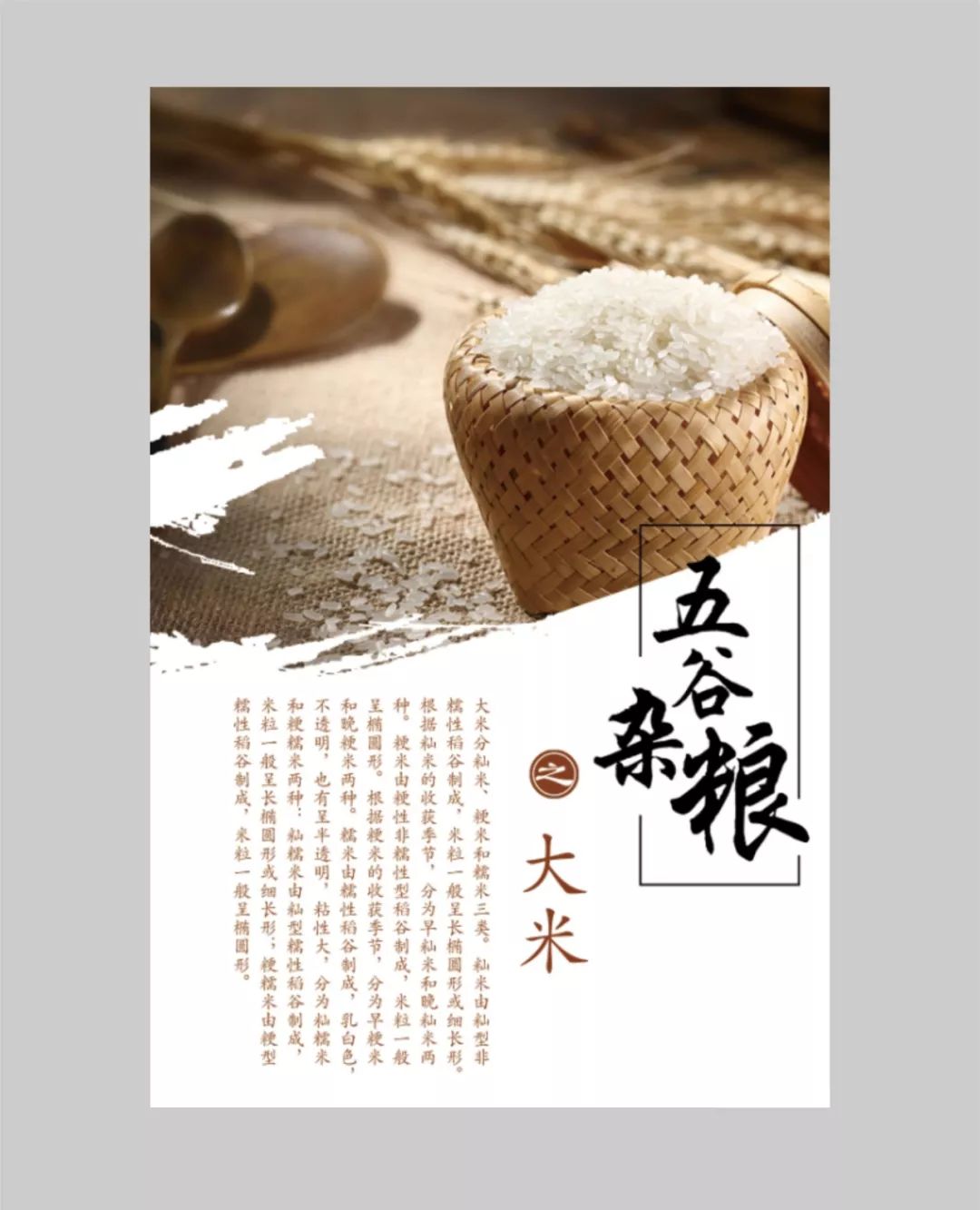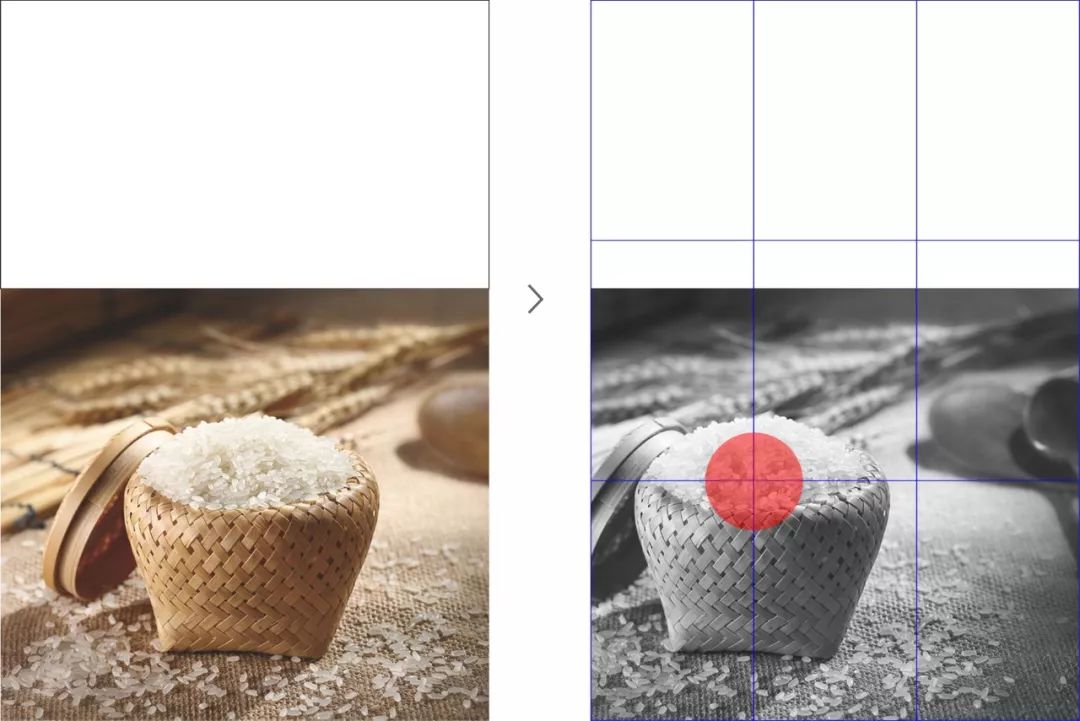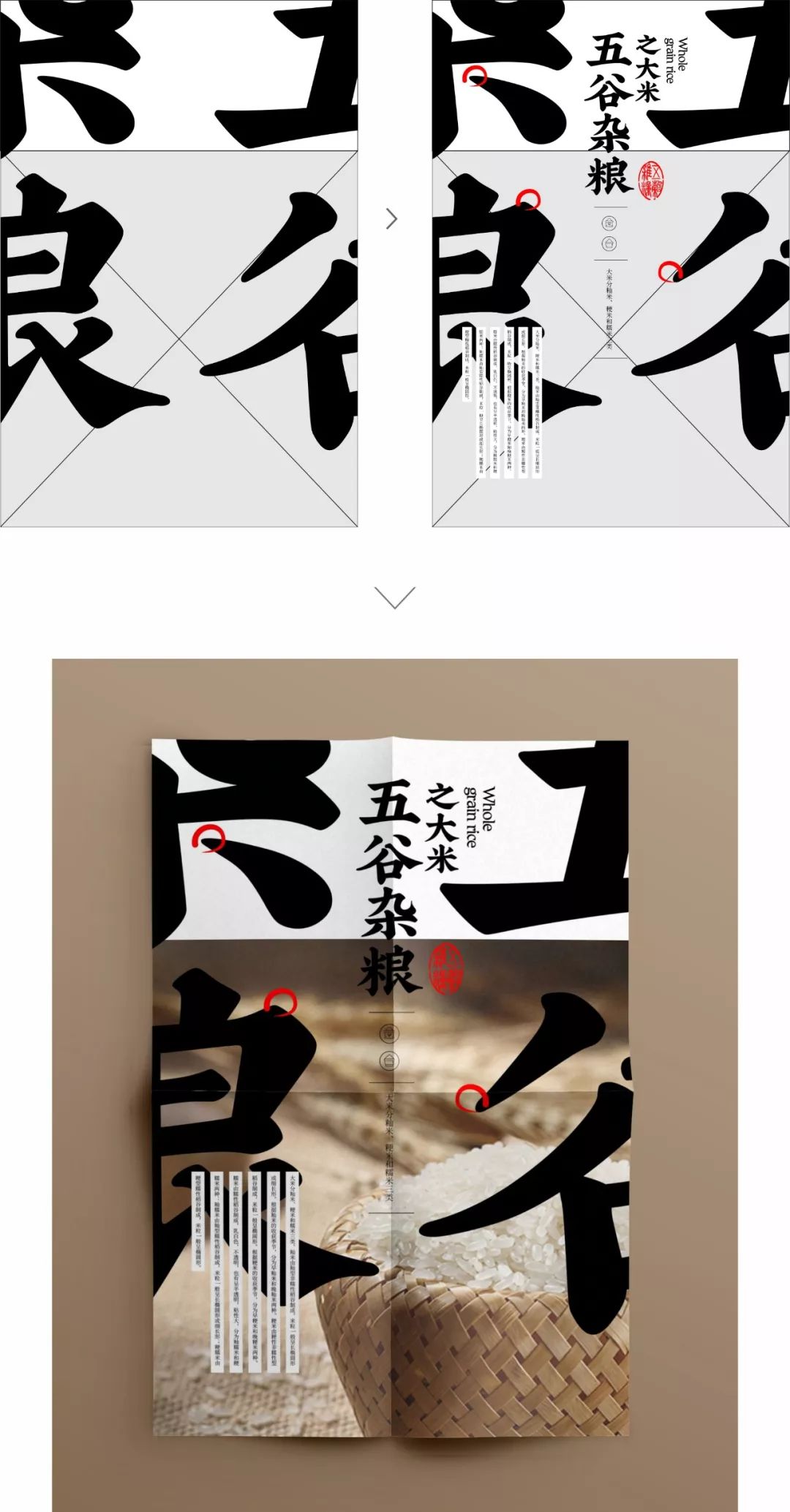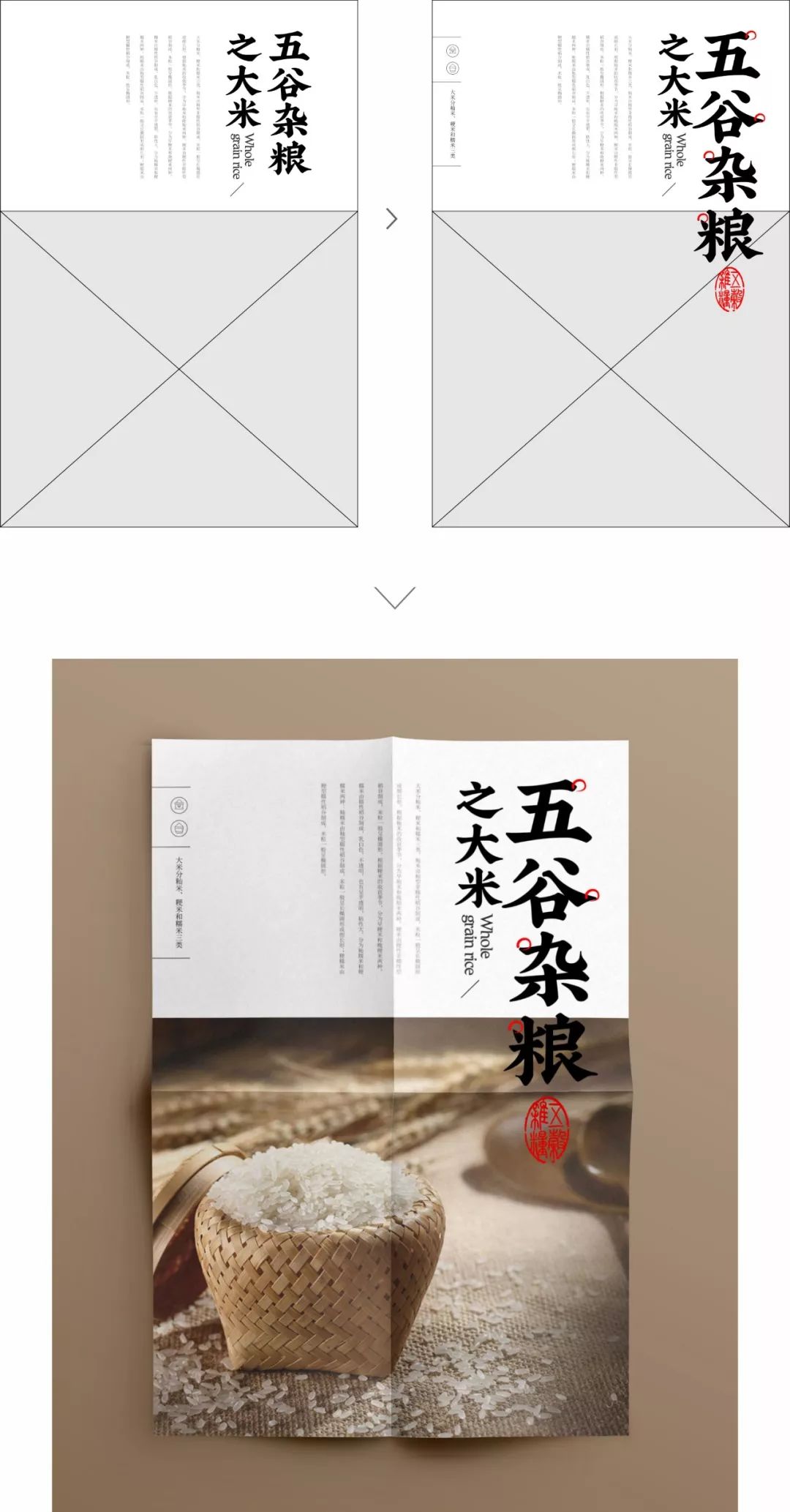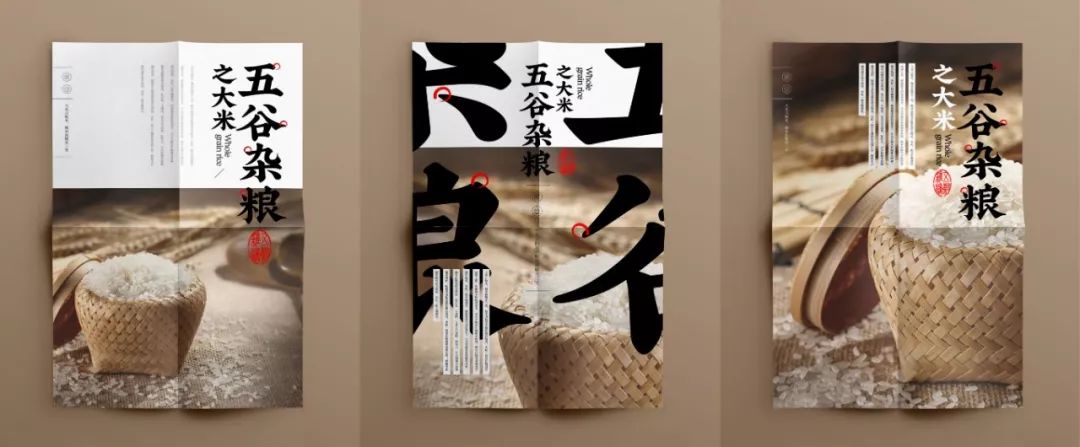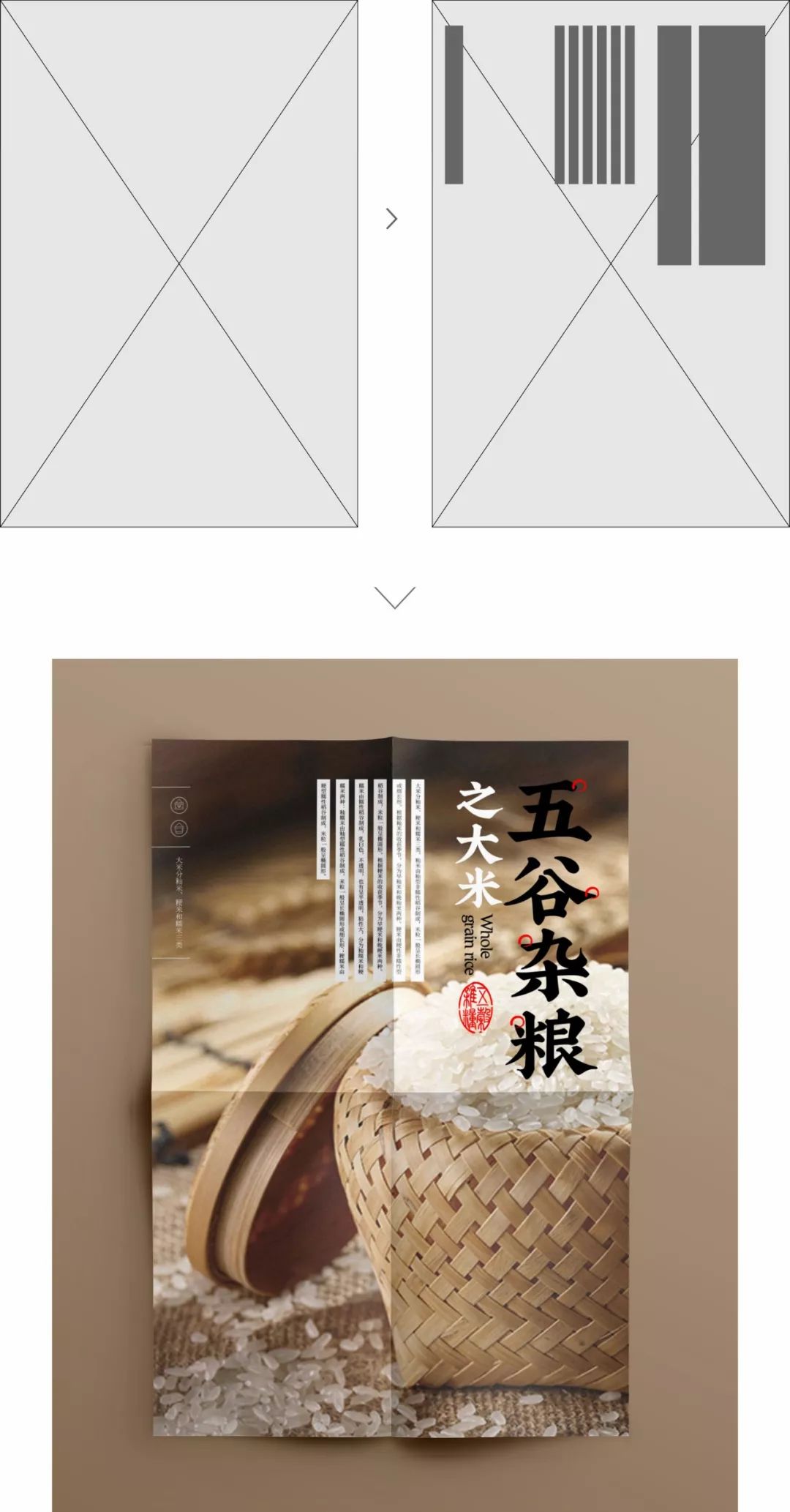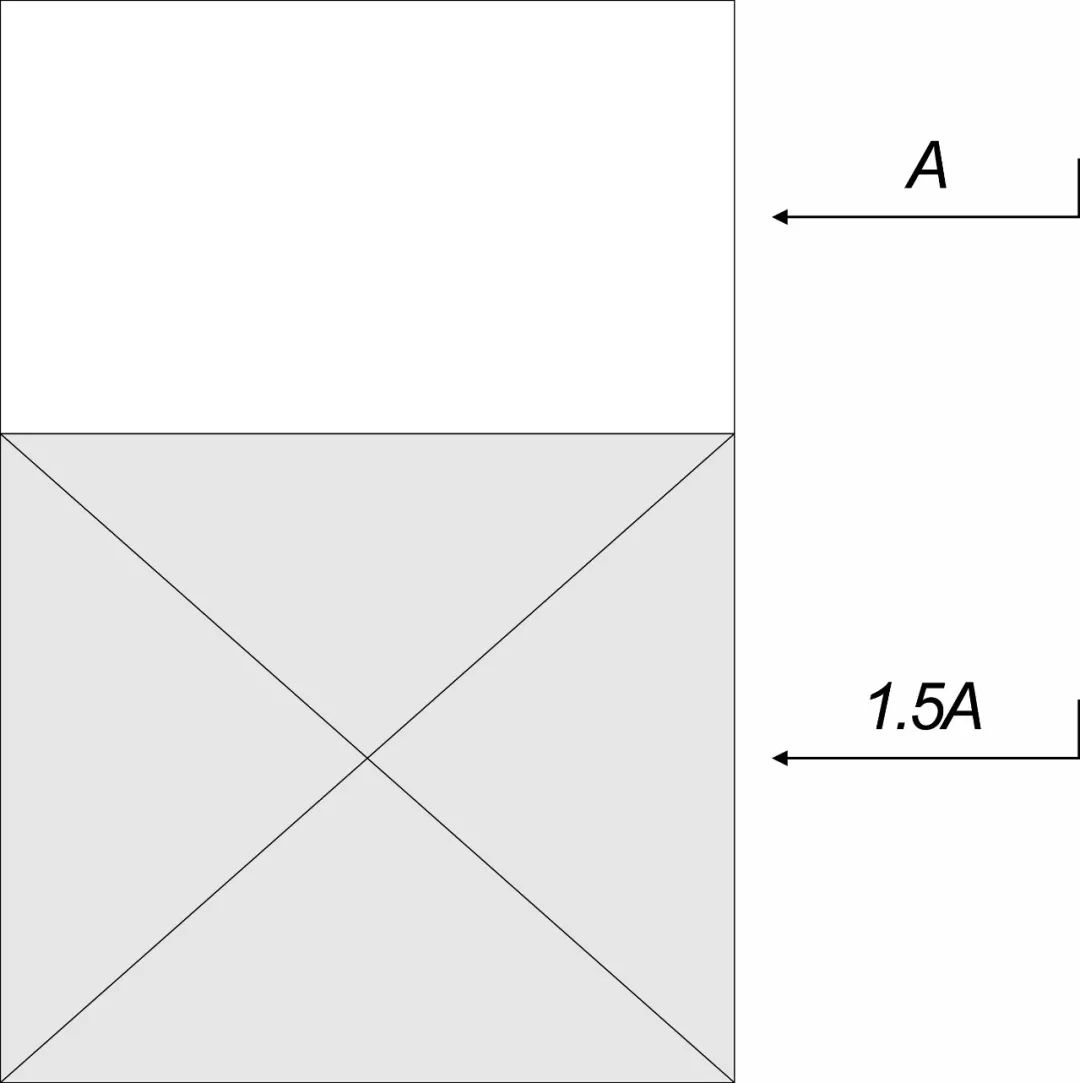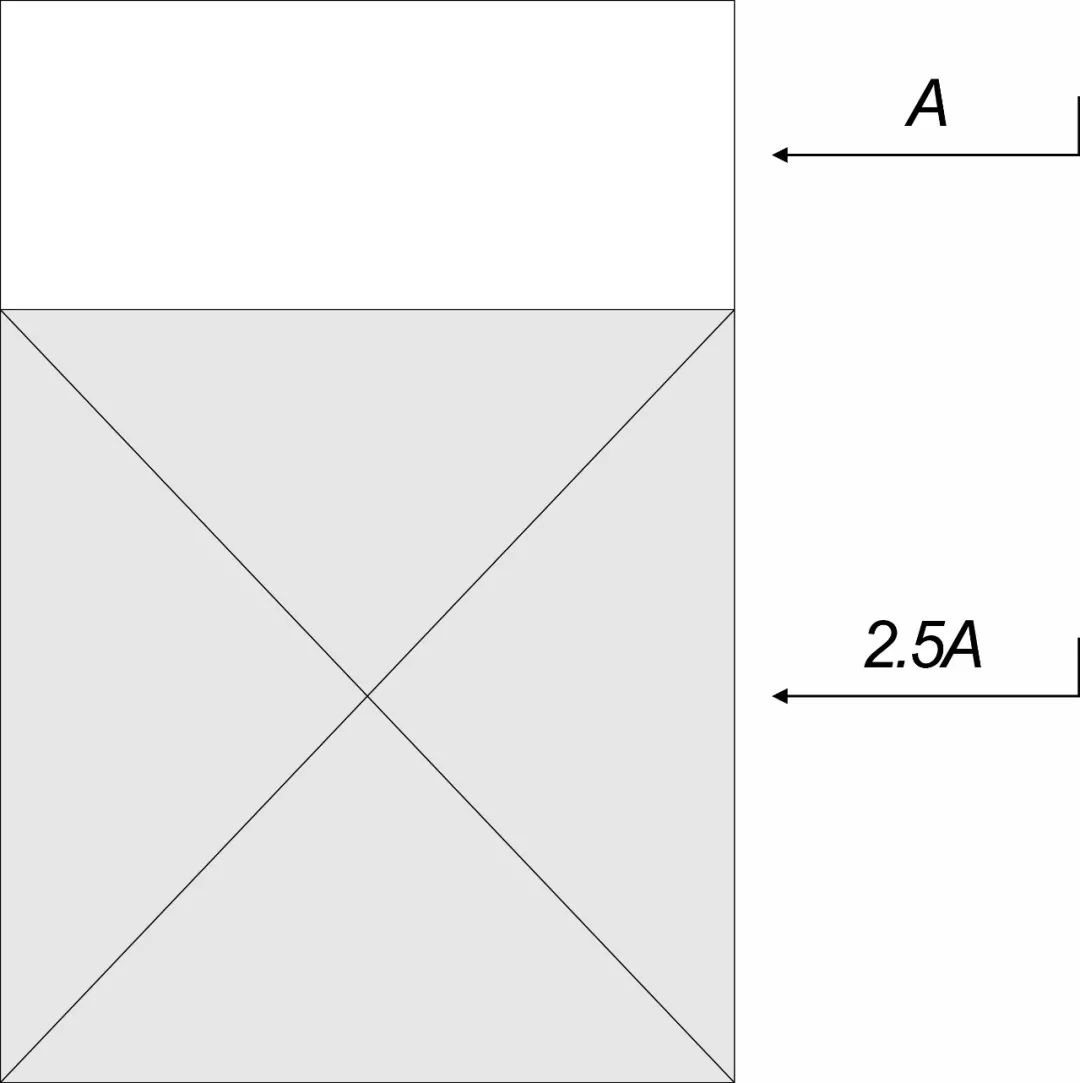
如何轻松做出多种海报方案?分享一个诀窍!
设计原稿 >
本期是诗人改稿专栏的第28期,我们首先来看一下设计原稿,整体有什么样的版式问题。
这个海报是关于五谷杂粮的设计,画面给人的感觉是不够精致,虽说不太杂乱,但是在信息的编排上,内文信息显然有点大了,究其原因也许就是由于信息不太多,设计师不知道如何去处理空间,单纯的去放大了内文信息,最终结果适得其反。
主标题的处理其实也是不够好,线框的添加并没有使信息变得规整,反而与承载图片的水墨笔触相互抵触干扰,造成视觉的生硬感。
“之大米”的文字间距过于疏,而且字体也不统一,在字体权重上与主标题也不是特别适合。
诗人改稿方案一 >
先确定一种版面构图形式,划分整体空间布局。如果想体现稳定平和的气质,可以选用上下或者左右分割构图。
确定上下构图的空间比例为1:1.5,下方灰色区域放置图片,以图片作为主体展开设计。
图片放在画面中其实并不难,但是哪个位置更加合适就需要考究了,这里运用(九宫格)三分构图法确定图片的核心位置。
主标题与副标题的字体保持统一,利用大小对比强化信息间的层级差异,主标题与下方图片形成了叠压效果,产生了位置上的关联,内在的关联性更强。
诗人改稿方案二 >
这次我们还是用上下分割构图去设计,把比例分配调整一下,同样会呈现不同的设计画面。
重新分配一下上下构图的空间比例为1:2.5,下方灰色区域放置图片,以图片作为主体展开设计。
将主标题进行符号化处理,放大其空间占比强化其视觉性,并与图片产生了位置上的关联,内文信息用色块承载体现其功能性。
诗人改稿方案三 >
前两种方案设计完毕,我们还可以继续发散思维,看是否还能做出更多方案。把比方说将画面做成满版构图。
满版构图的形式会使得画面的氛围感和融入感更强,把一个事物放大到极致从另一个层面来说属于近距离视觉的构图形式,让其局部特征凸显的更清晰,这在电商详情页中用的也是比较多,常用来表达商家对产品质量的自信,增强受众的信赖感。
调整方案
最后总结 >
学习是有方法的,引导也是要有思路,毕竟我们每天都面临许许多多的不同种类的设计,不论哪一种方式,都不能去完全否定其思路。引导永远是第一位,发现不足,找到属于自己的设计,毕竟没有哪一种风格是最好的。